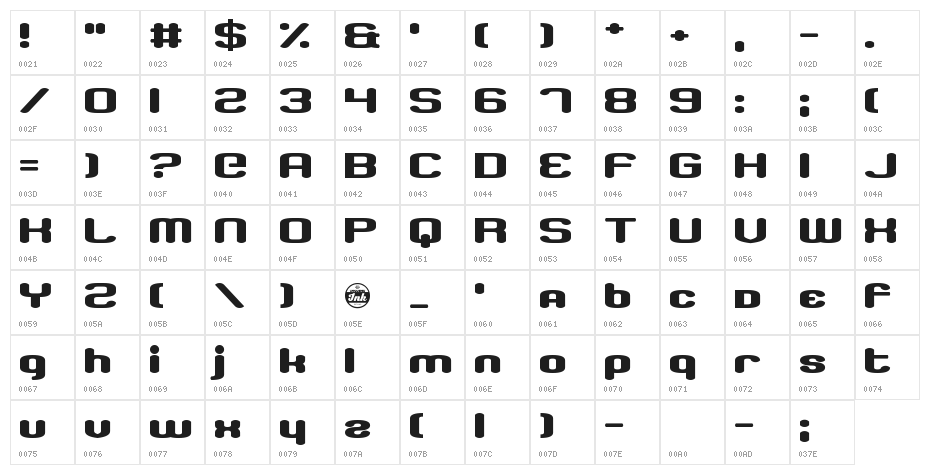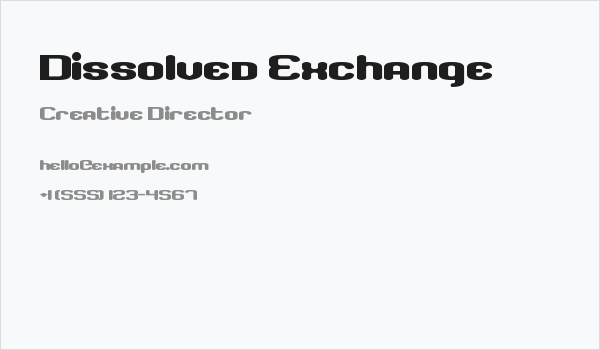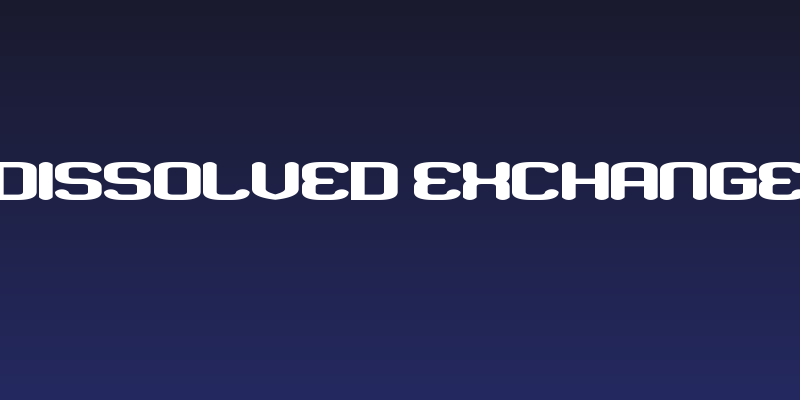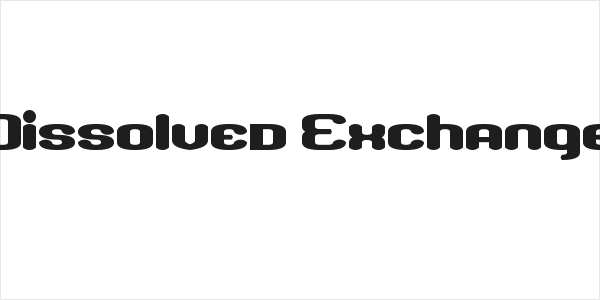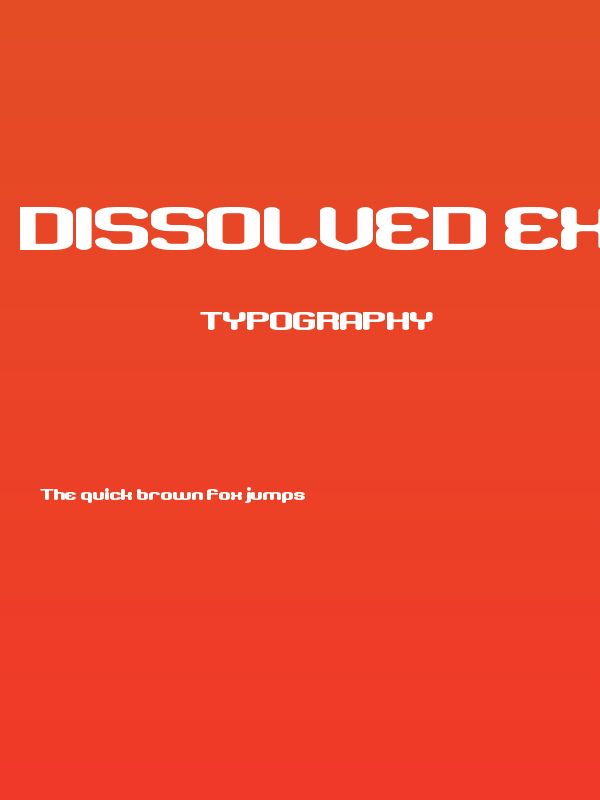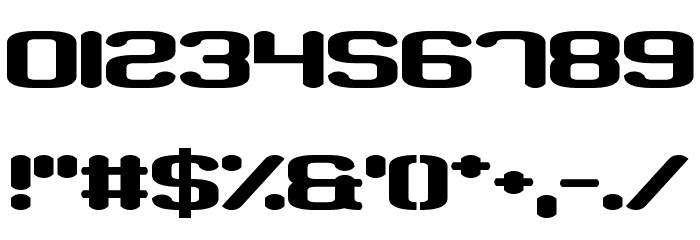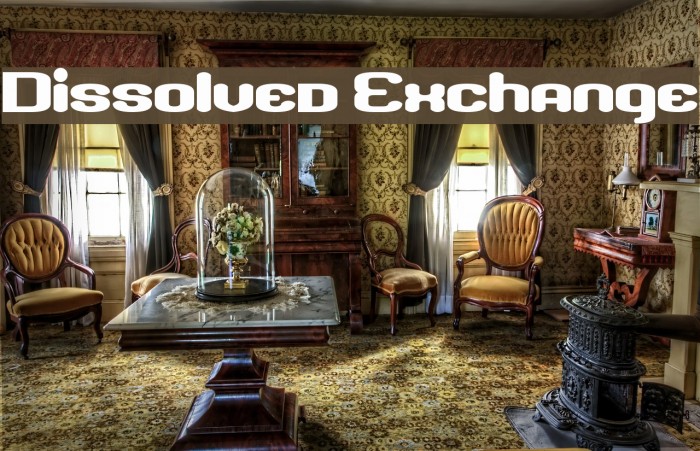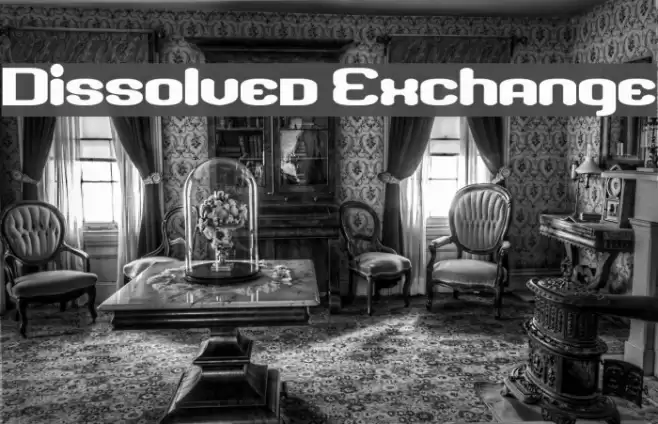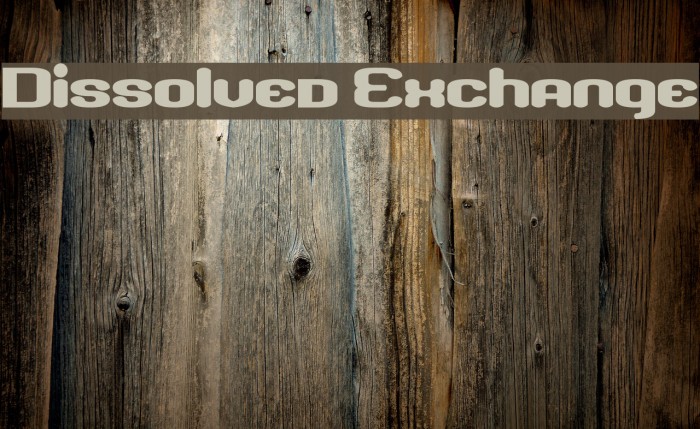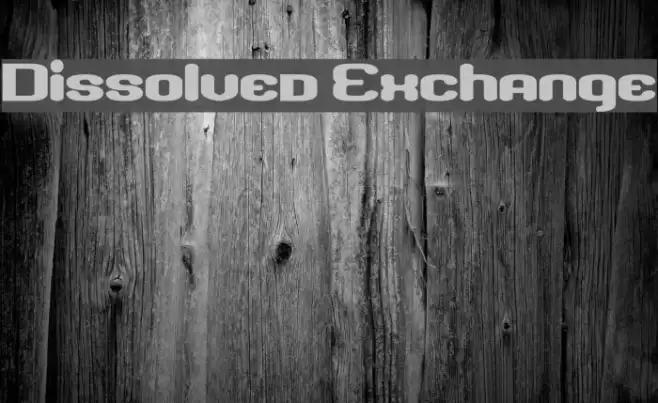
Dissolved Exchange Font
| Projets proposés | Ideal for technology branding, futuristic posters, video game titles, and modern advertising campaigns. |